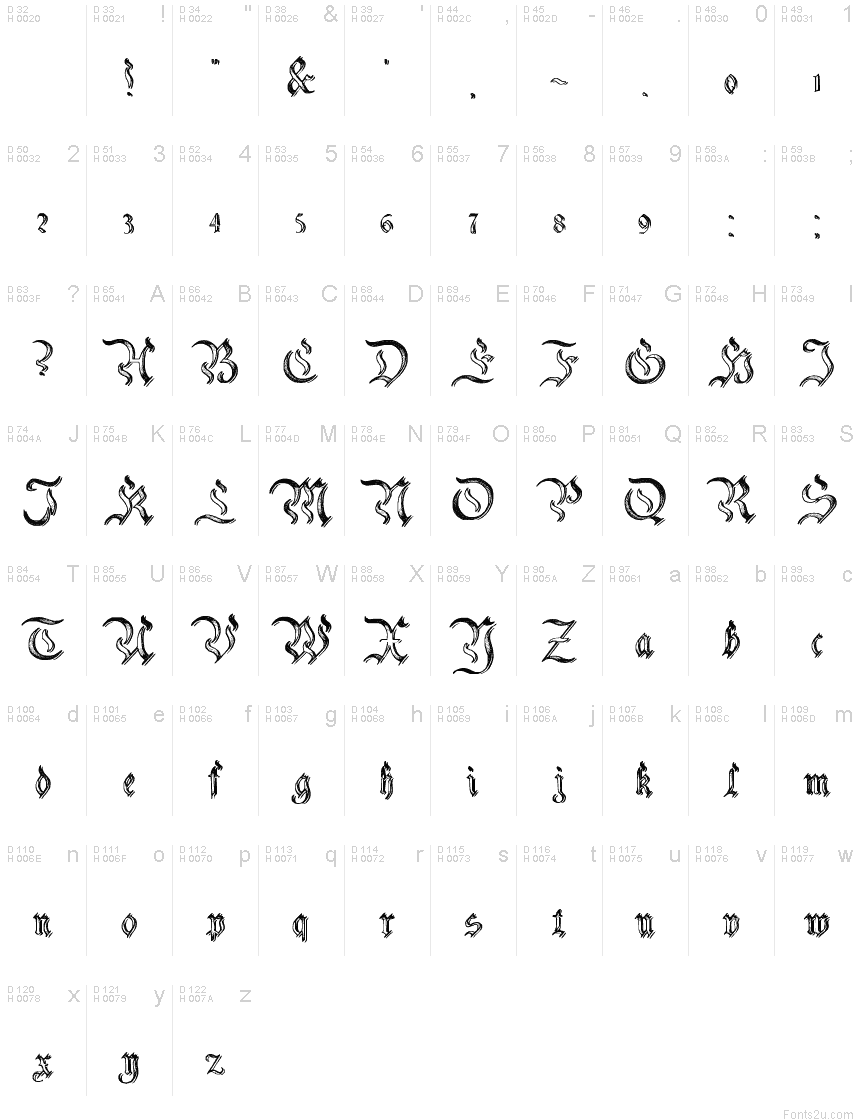
Charterwell No2 od PJL to darmowy gotycki krój pisma, który wygląda, jakby został wyryty prosto w drewnie. Litery są wysokie, wąskie i pełne ostrych kątów, a wypełniające je szrafowanie nadaje im surową, ręcznie rzeźbioną teksturę. Całość jest mroczna, ceremonialna i nieco buntownicza – niczym napisy na drzwiach starej katedry czy okładka winyla z metalem.
Ten darmowy font świetnie sprawdzi się na okładkach książek fantasy, w brandingu RPG lub LARP, logotypach zespołów, plakatach na festiwale historyczne, wzorach dla tatuażystów czy klimatycznych miniaturach na YouTube. Użycie Charterwell No2 w większym rozmiarze pozwala w pełni docenić jej drapiącą teksturę, natomiast połączenie z prostym, nowoczesnym bezszeryfowym krojem pisma w mniej istotnych tekstach zapewni czytelność i wyrazisty efekt.